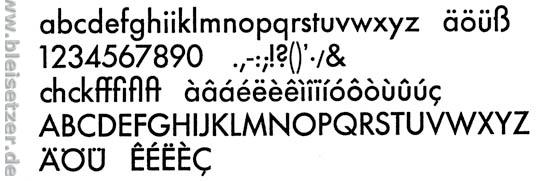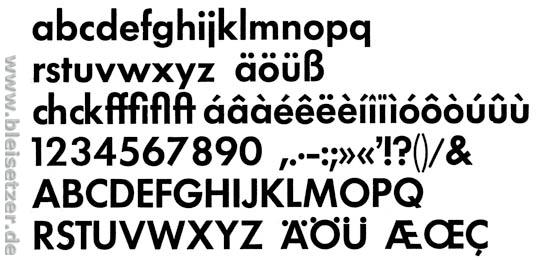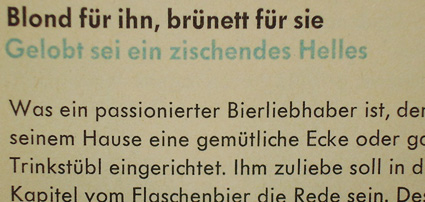
Das ist ein Original aus den 50ern. Ich möchte diesen Stil nachahmen und wissen, welche Schrift man da am besten benutzt.
Hm. Ich hab das Gefühl, das kleine "s" passt nicht richtig. Aber da gibt es ja unzählige Hersteller ...
Doch, das ist die Futura dreiviertelfett und die Futura Buchschrift:
Bauersche Gießerei, Frankfurt am Main
Erstguß 1927 und 1930
Paul Renner
Nachsatz an Georg: Welches digitale Produkt ist es dann eigentlich geworden? Und wie sind die Erfahrungen damit? Oder habe ich etwas überlesen?